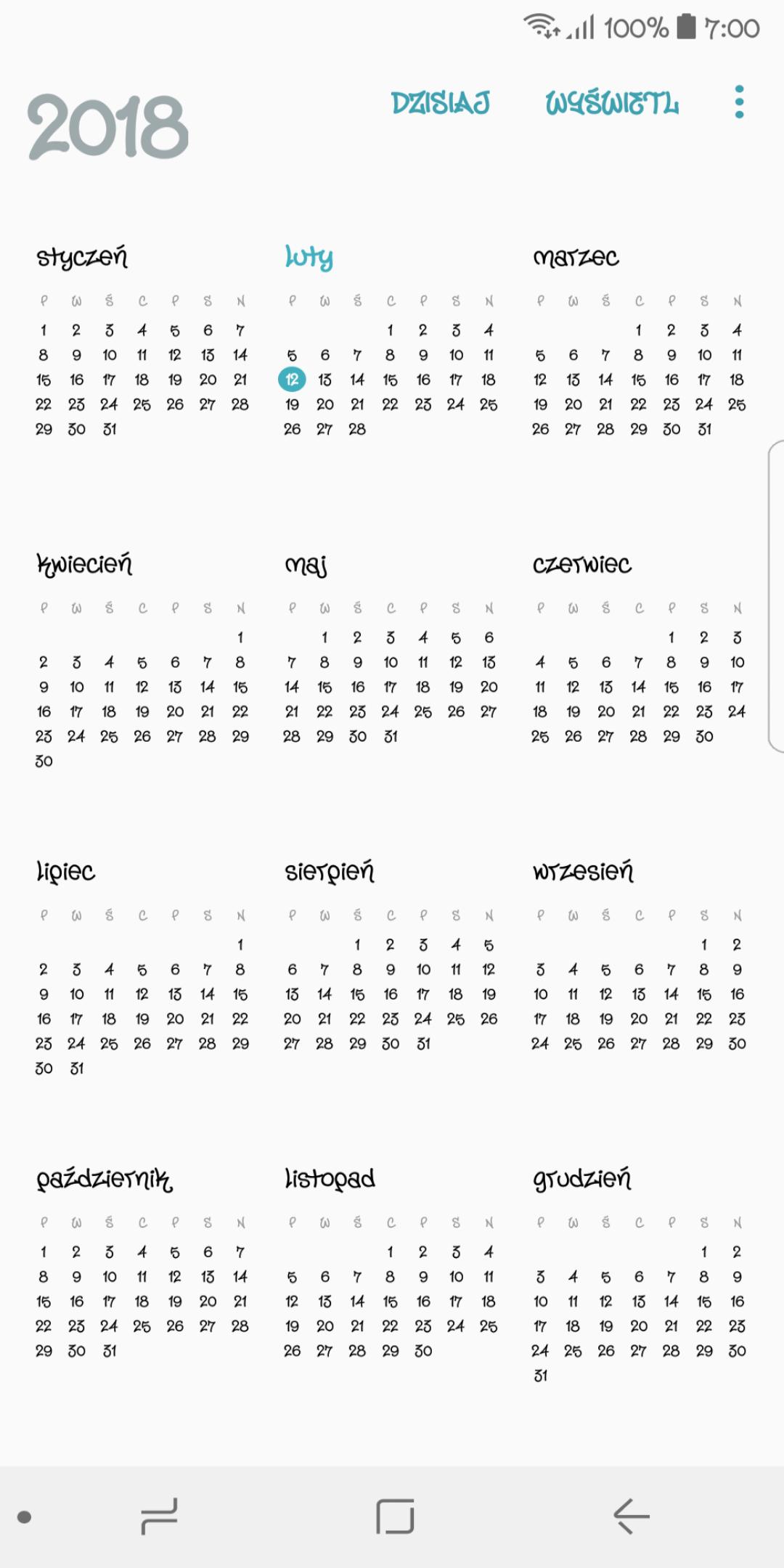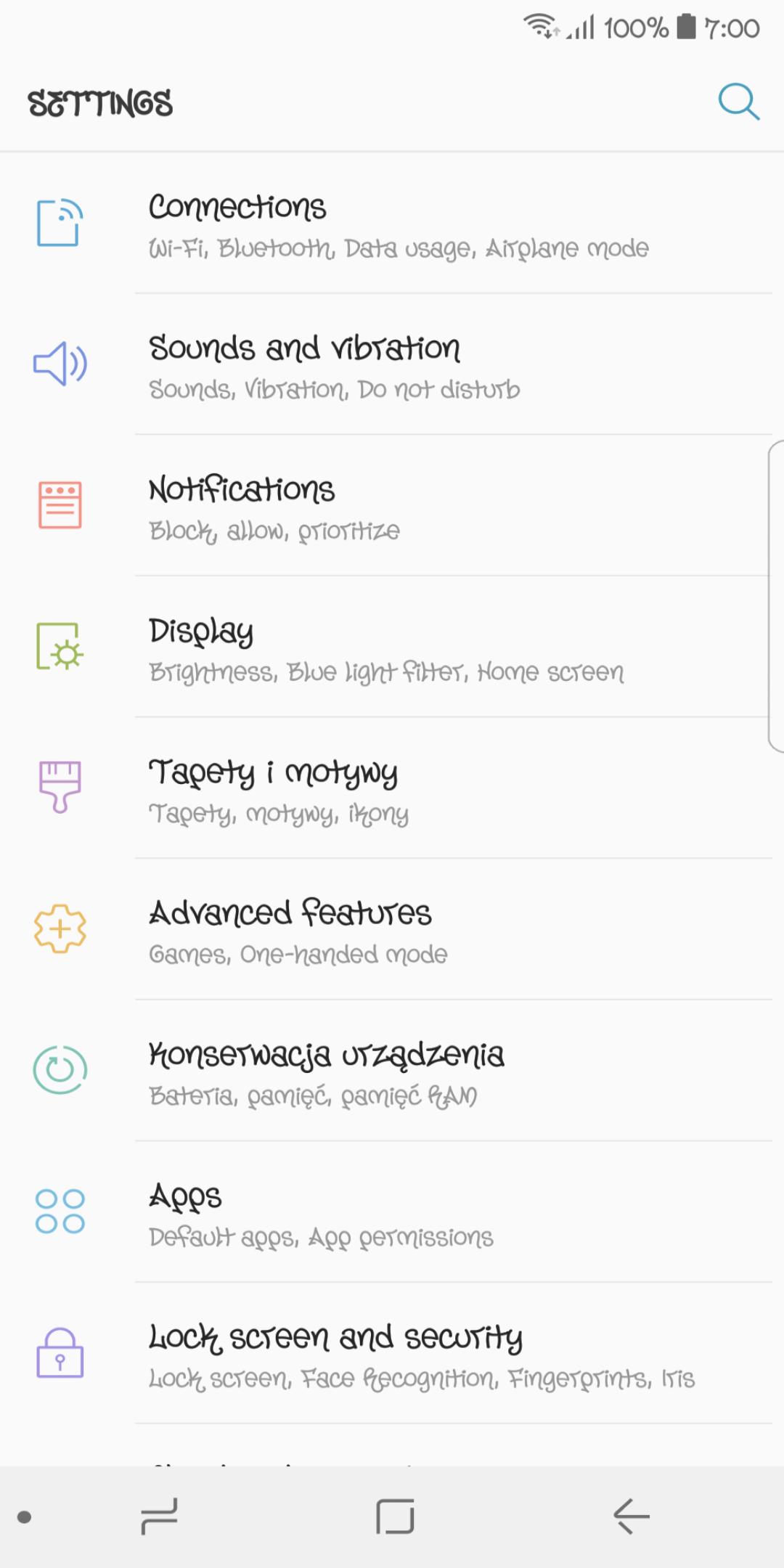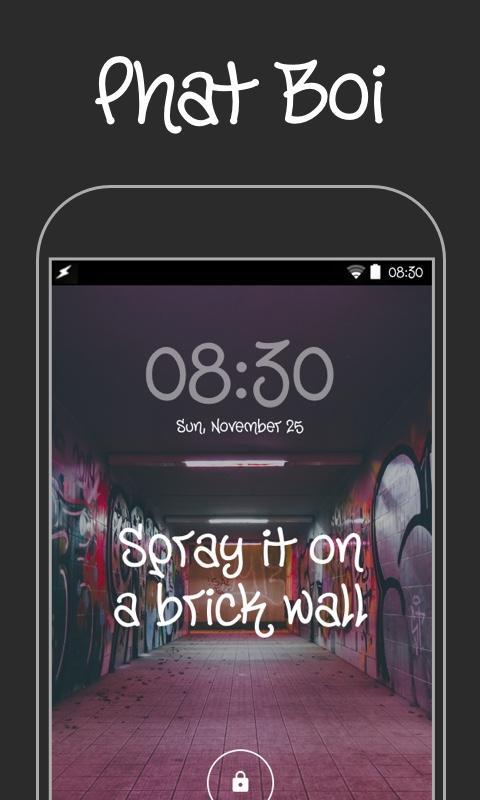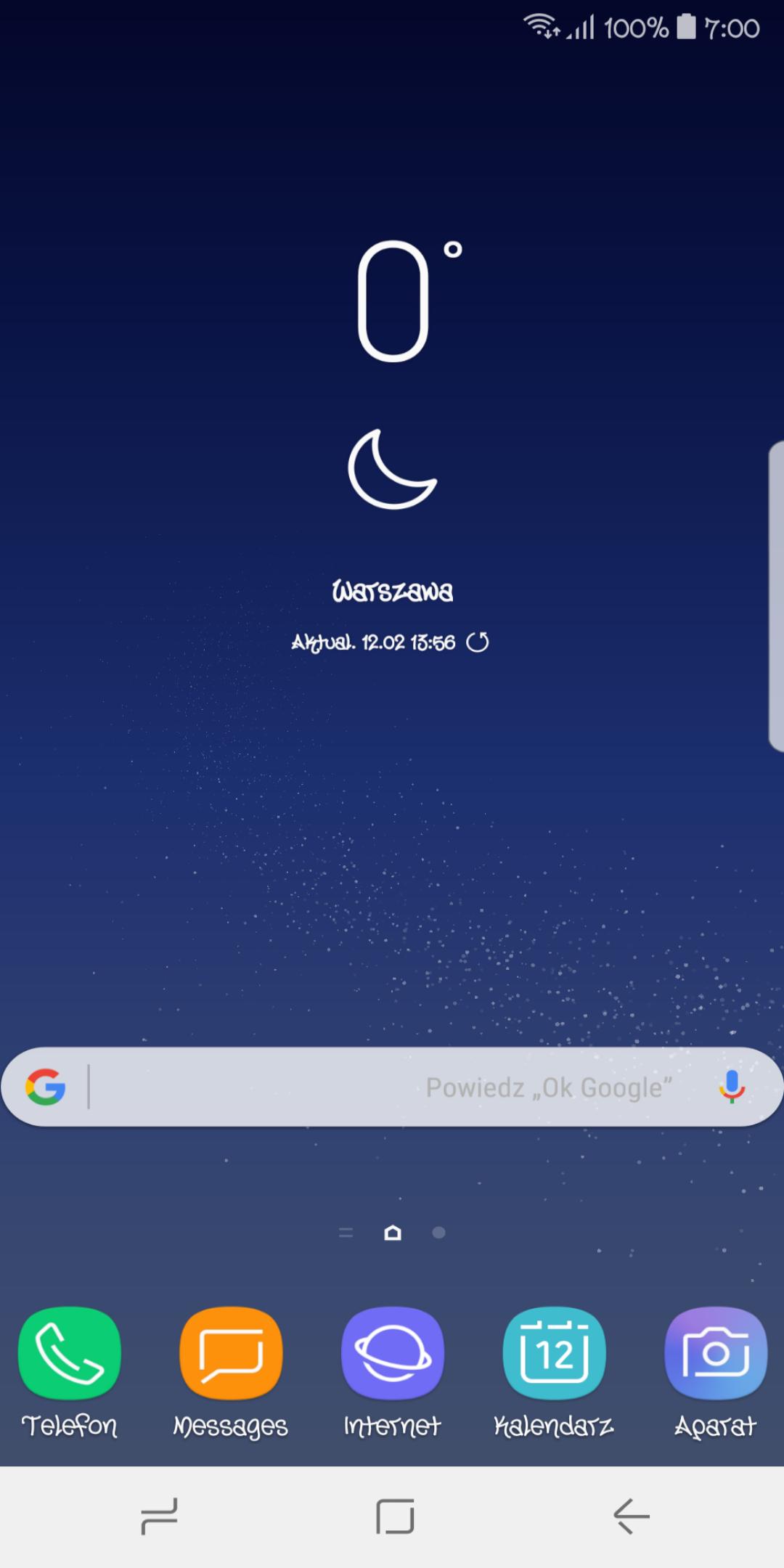
O Phat Boi Polsku FlipFont
Kanciasta, tłusta i energiczna; czcionka Phat Boi™ jest po prostu wystrzałowa. Jeśli potrzebujesz wyróżniającej się czcionki, to jest właśnie ta. Na co więc czekasz? Nadaj nowy styl urządzeniu i popisz się tą nową czcionką.